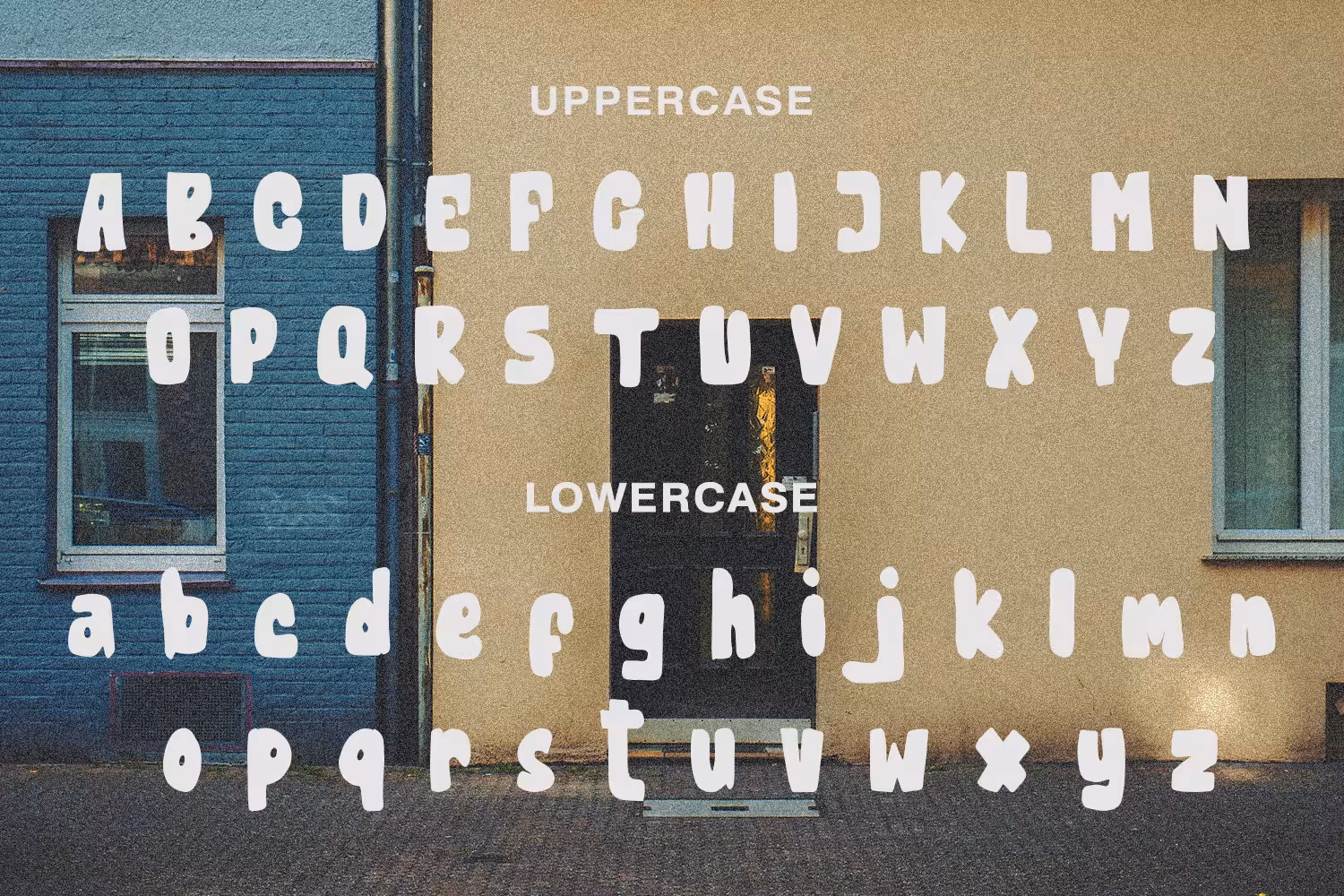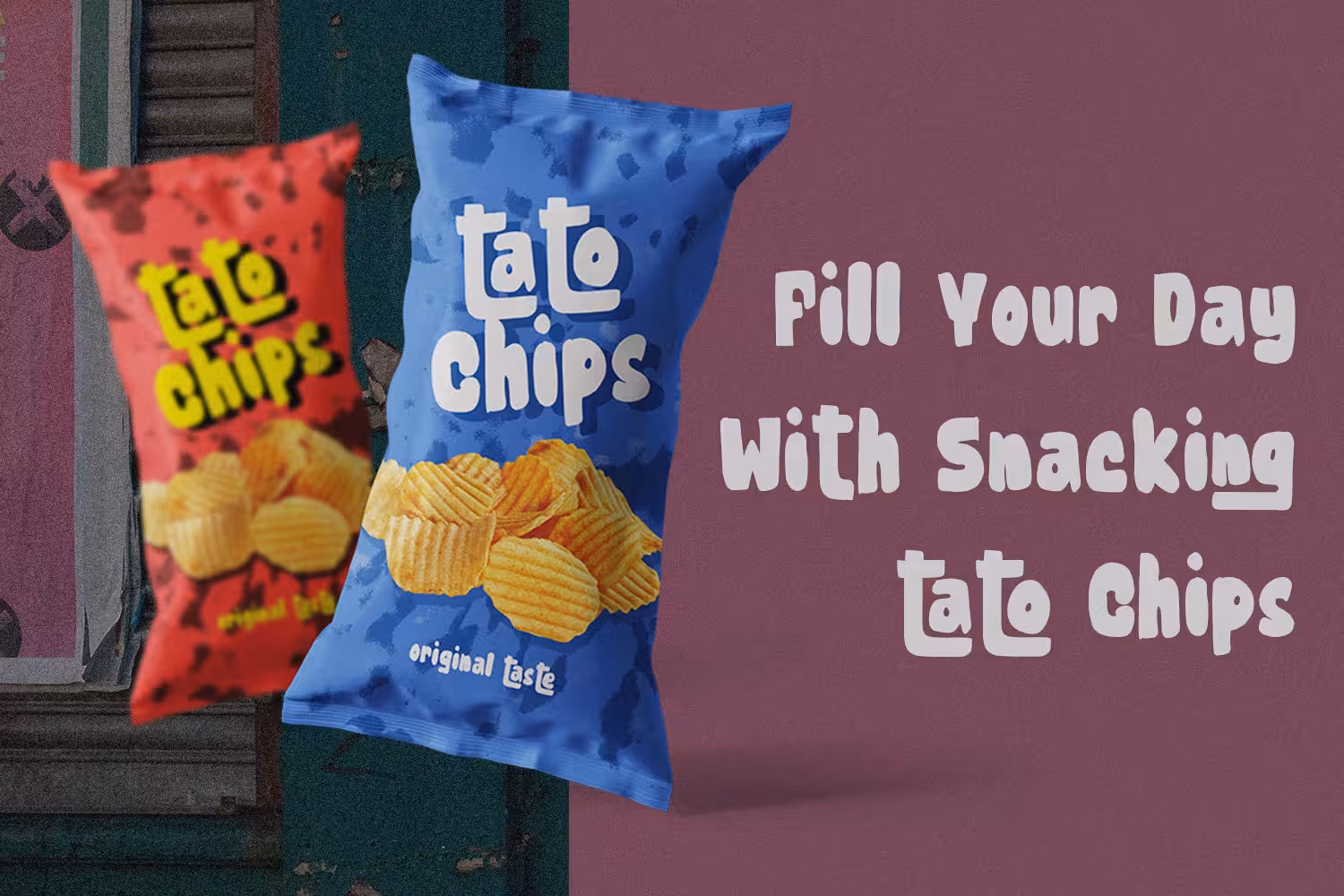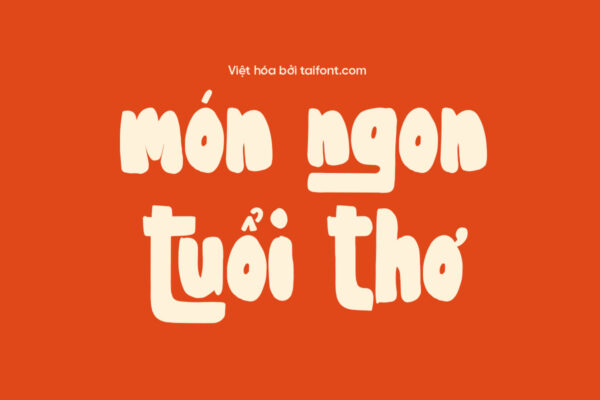
Giới thiệu về Font TF Harlem Boston Việt hóa
TF Harlem Boston Việt hóa là một font chữ nổi bật với thiết kế béo tròn, phóng khoáng và đầy ngẫu hứng. Font này mang đến vẻ ngoài vui tươi, dễ thương và rất thân thiện, với những nét chữ tự do, không theo khuôn mẫu nghiêm túc, lý tưởng để tạo điểm nhấn độc đáo và thu hút mọi ánh nhìn trong các thiết kế đòi hỏi sự đáng yêu, gần gũi và một chút phá cách.
Với đặc điểm là hình dáng tròn mập mạp, nét chữ tự do và tính thẩm mỹ cao, Harlem Boston là lựa chọn hoàn hảo cho các thiết kế muốn truyền tải sự trẻ trung, dễ thương và sự gần gũi, đặc biệt là trong các lĩnh vực:
- Thiết kế ẩm thực: Hoàn hảo để sử dụng trên tiêu đề menu, logo nhà hàng, quán ăn hoặc các ấn phẩm quảng cáo liên quan đến thực phẩm, đặc biệt là đồ ăn vặt, kem, bánh ngọt. Nét chữ béo tròn của font giúp món ăn trở nên hấp dẫn và nổi bật, gợi cảm giác ngon miệng và vui vẻ.
- Thiết kế cho trẻ em: Lý tưởng để sử dụng trên bìa sách, tiêu đề chương, hoặc các lời dẫn trong các cuốn sách, truyện tranh, truyện cổ tích dành cho trẻ em. Font này giúp tạo không khí thân thiện, vui tươi và thu hút sự chú ý của các bạn nhỏ.
- Thiết kế bao bì sản phẩm: Phù hợp để sử dụng trên nhãn mác, bao bì của các sản phẩm dành cho trẻ em, đồ chơi, đồ ăn vặt, hoặc các sản phẩm có phong cách vui tươi. Font này giúp sản phẩm trở nên nổi bật và thu hút.
- Thiết kế logo và nhận diện thương hiệu: Phù hợp cho các thương hiệu muốn truyền tải sự thân thiện, năng động và một chút phá cách, đặc biệt là các thương hiệu liên quan đến giải trí, ẩm thực, hoặc các sản phẩm sáng tạo.
Với TF Harlem Boston Việt hóa, bạn có thể dễ dàng thổi hồn vui tươi, sự đáng yêu và vẻ đẹp độc đáo vào các thiết kế, tạo ra những sản phẩm không chỉ đẹp mắt mà còn đầy cảm xúc và sức hút đặc biệt.